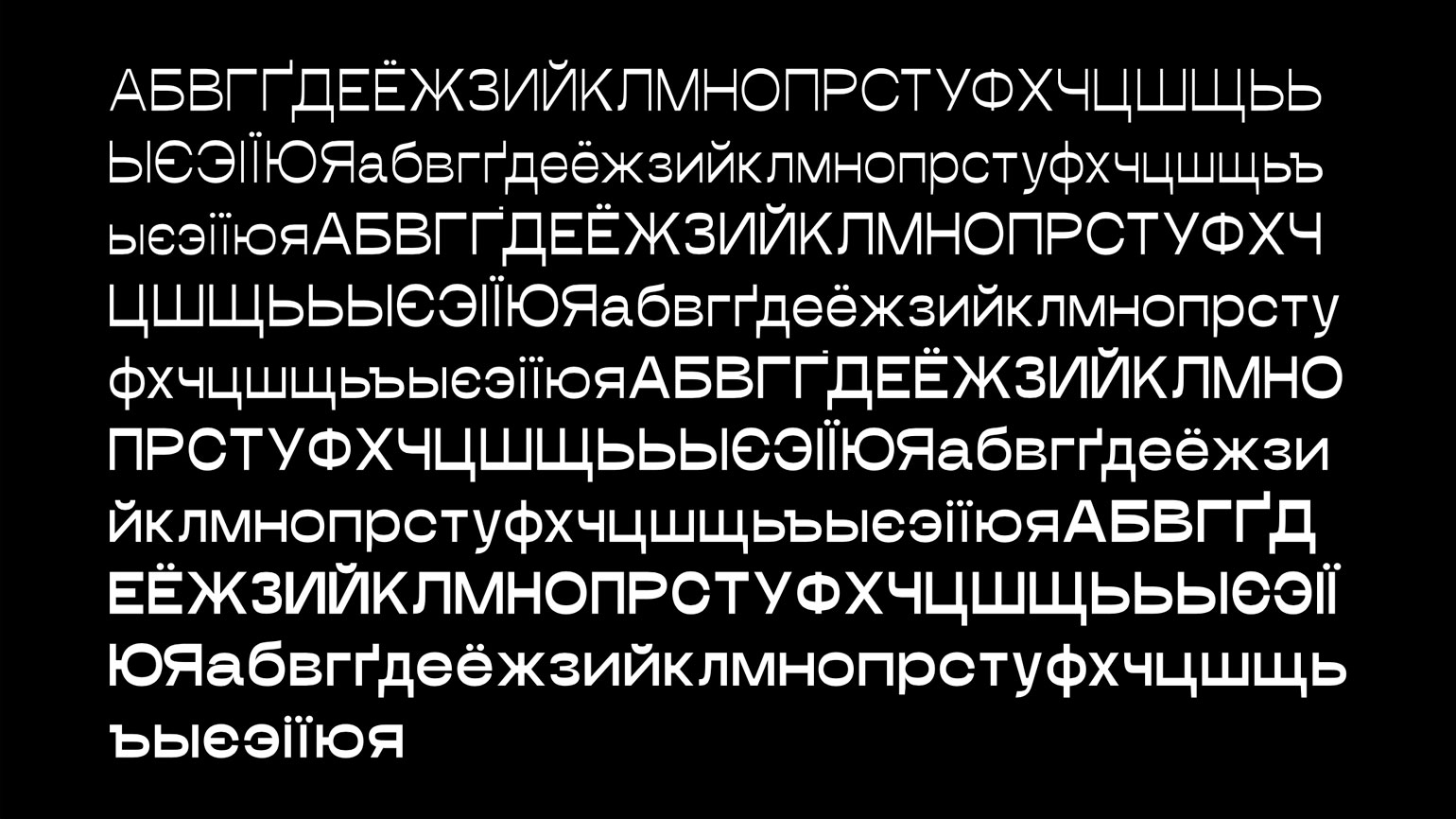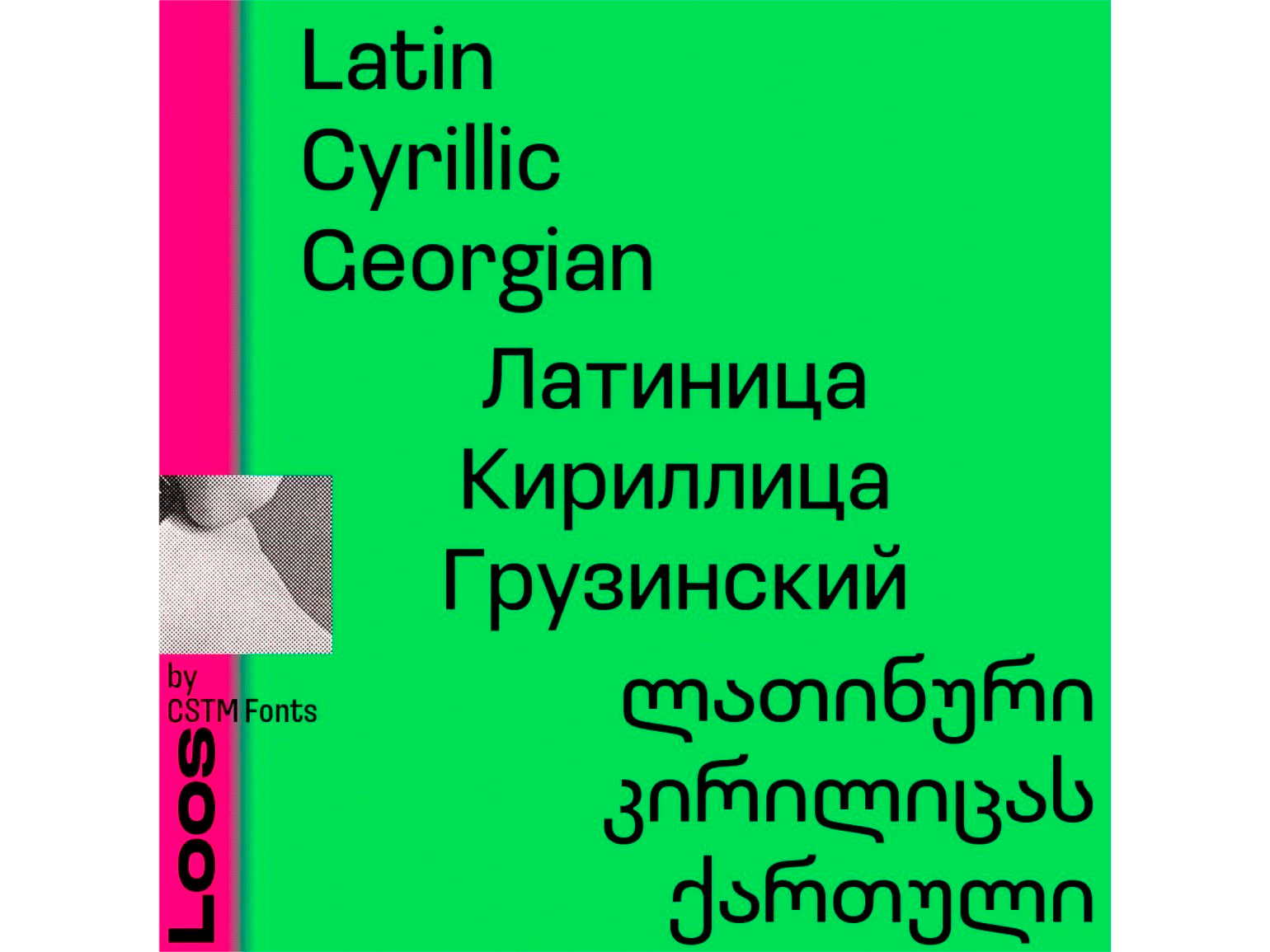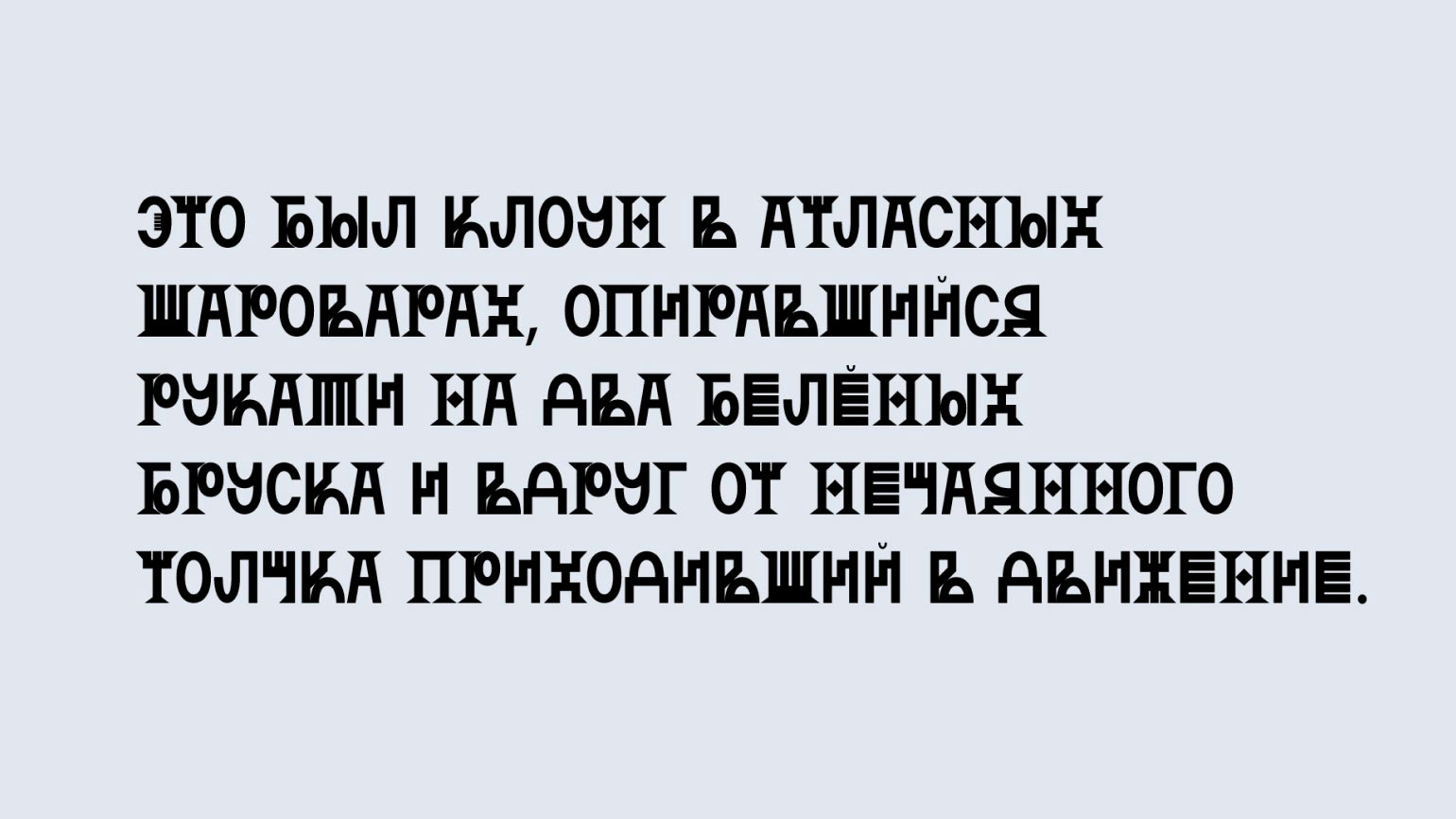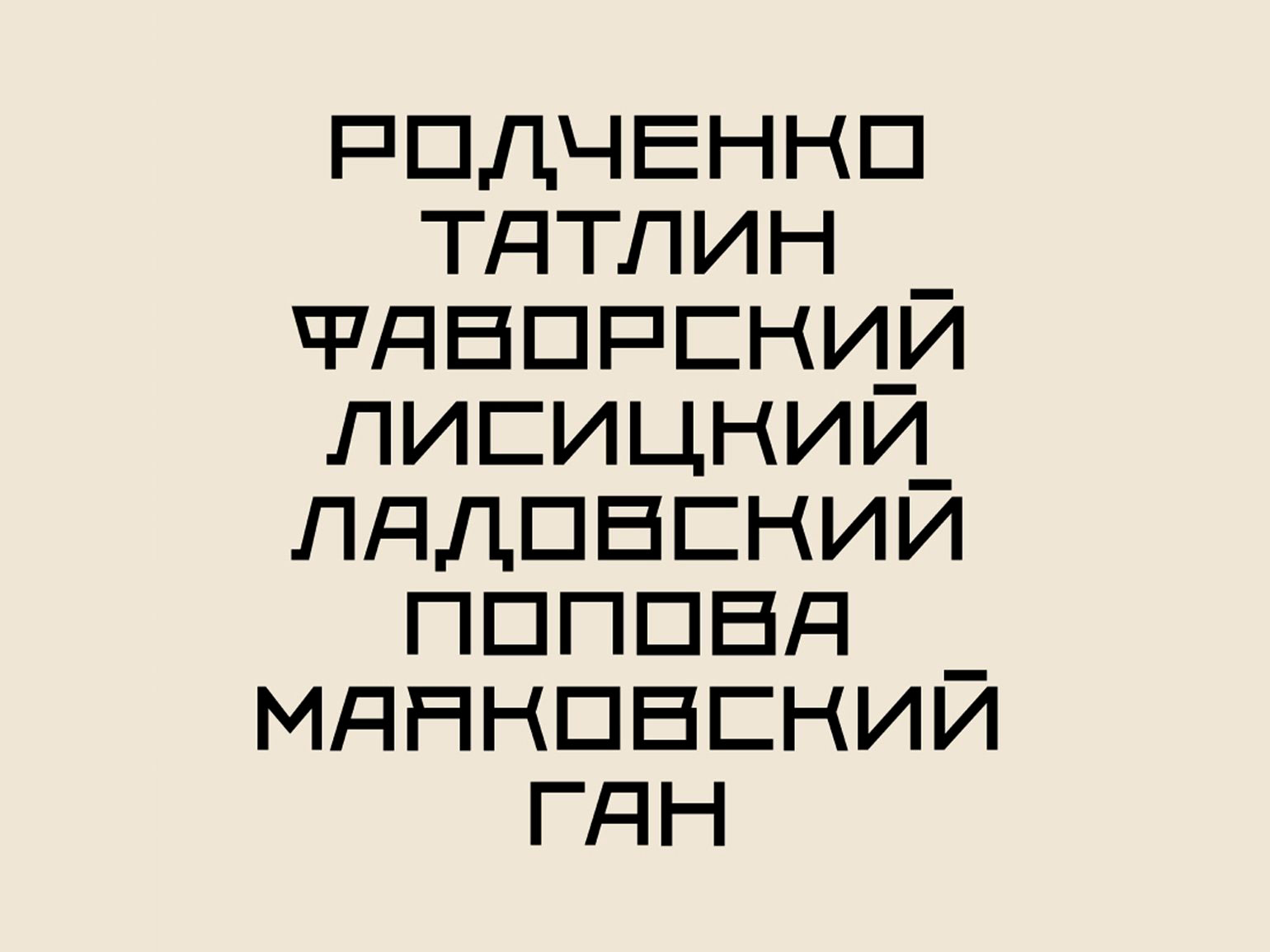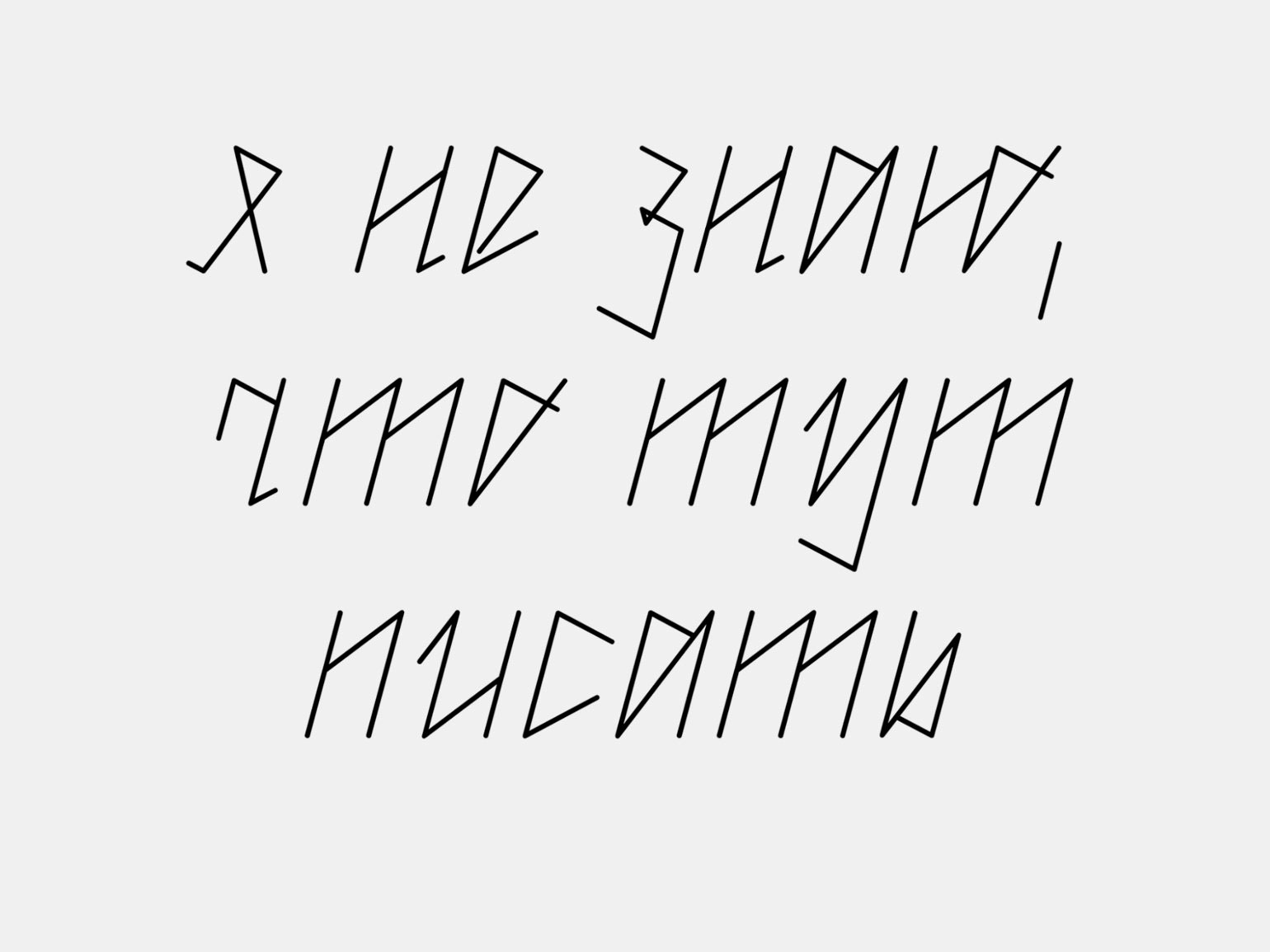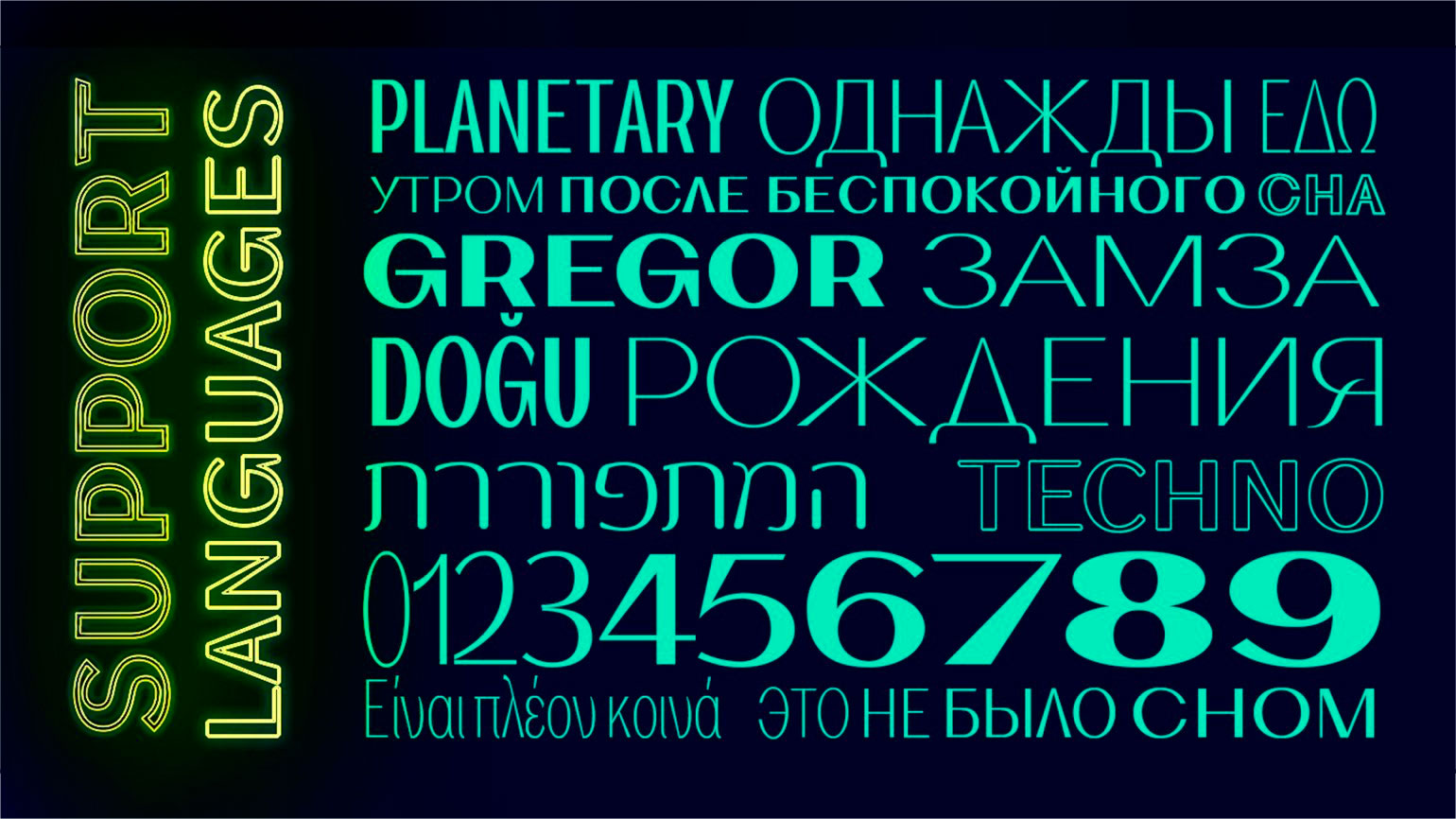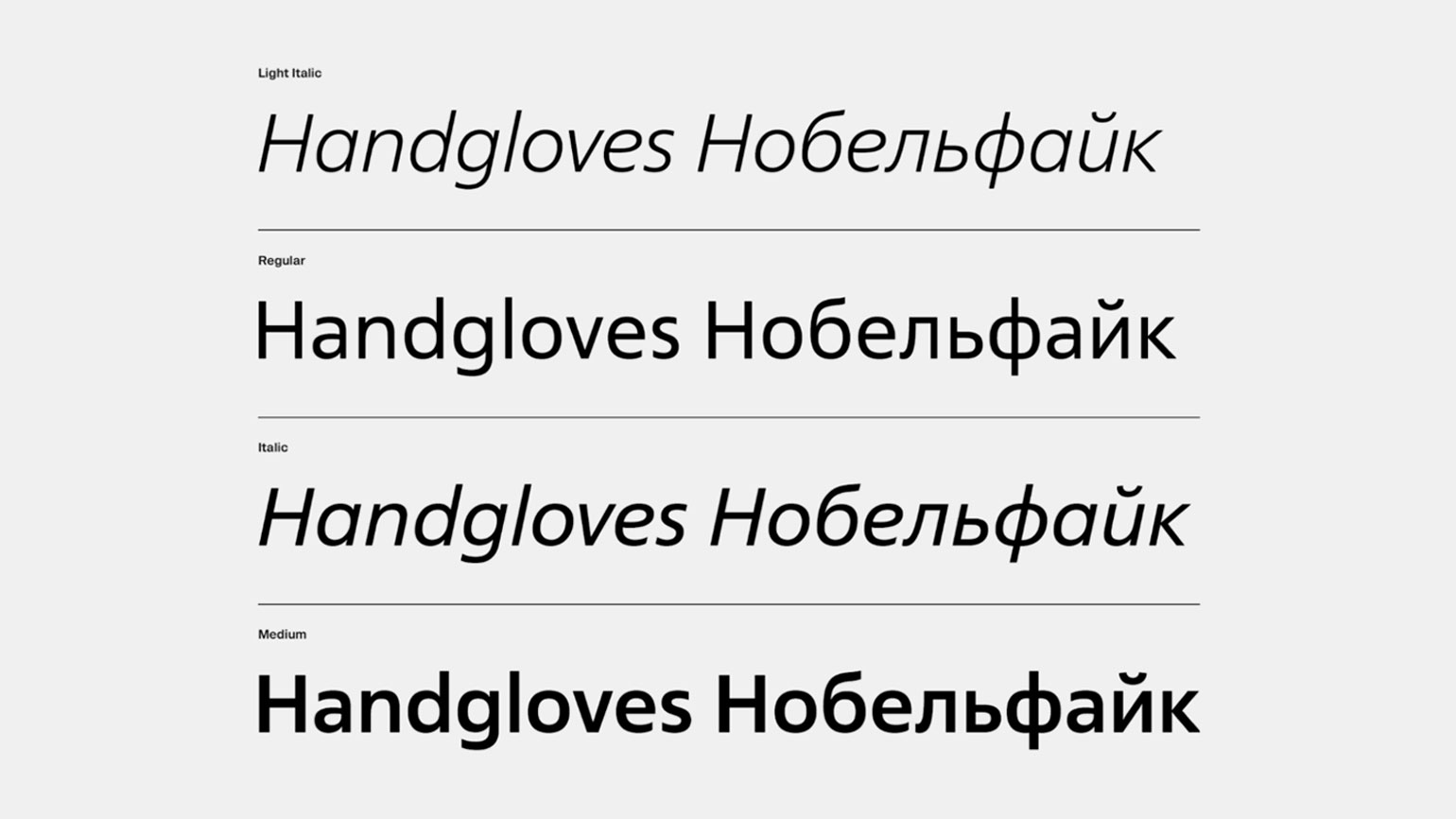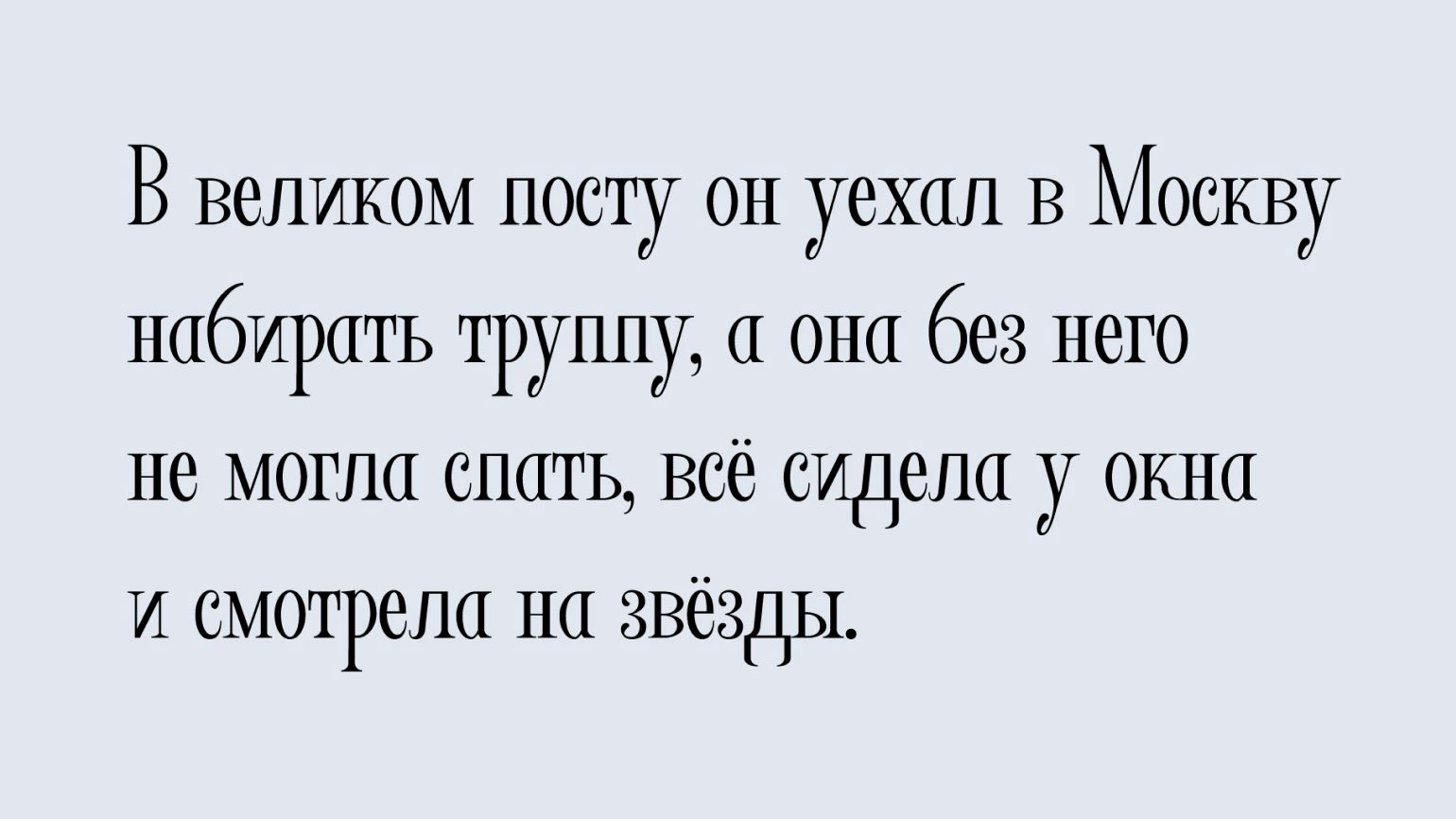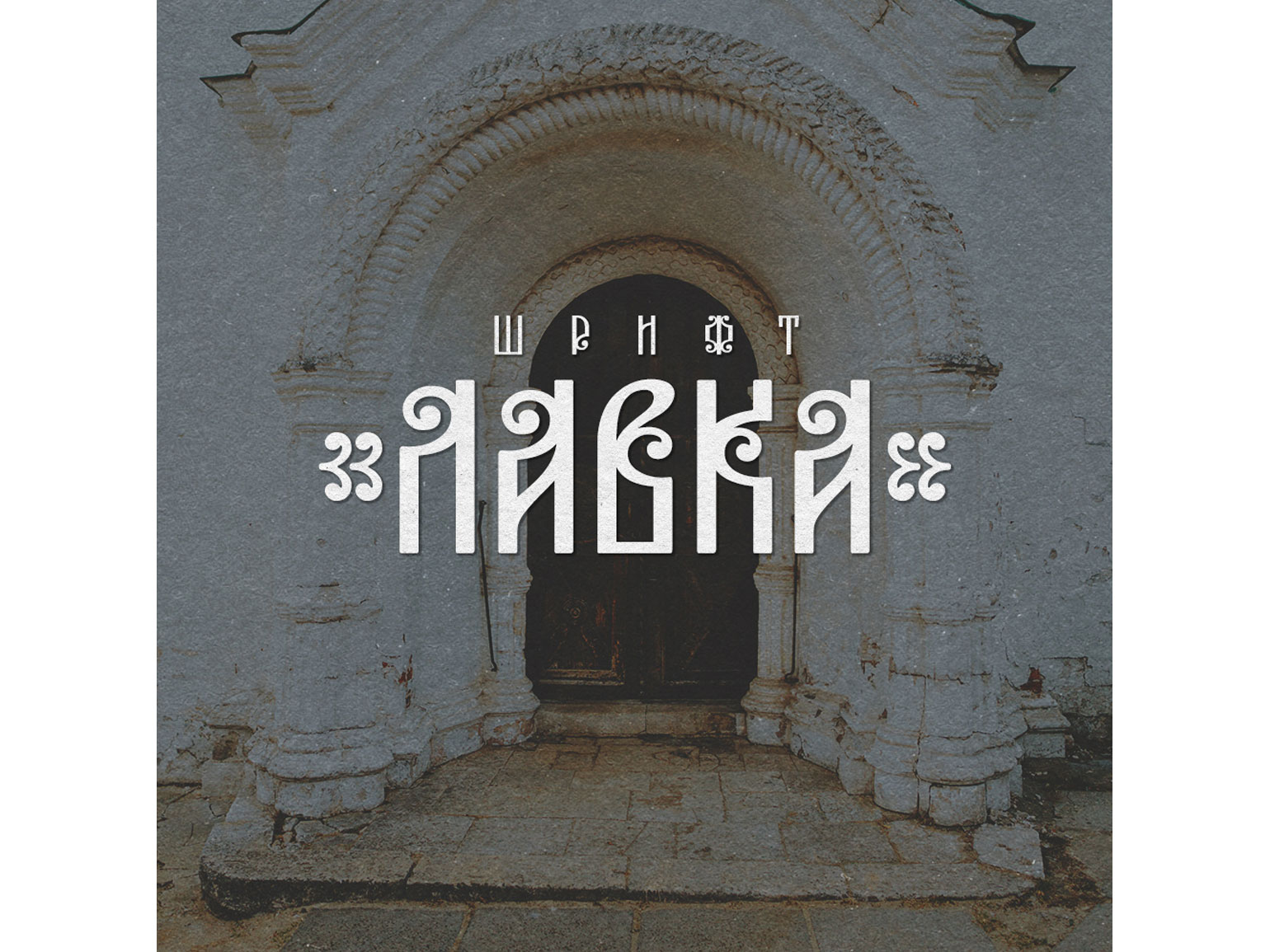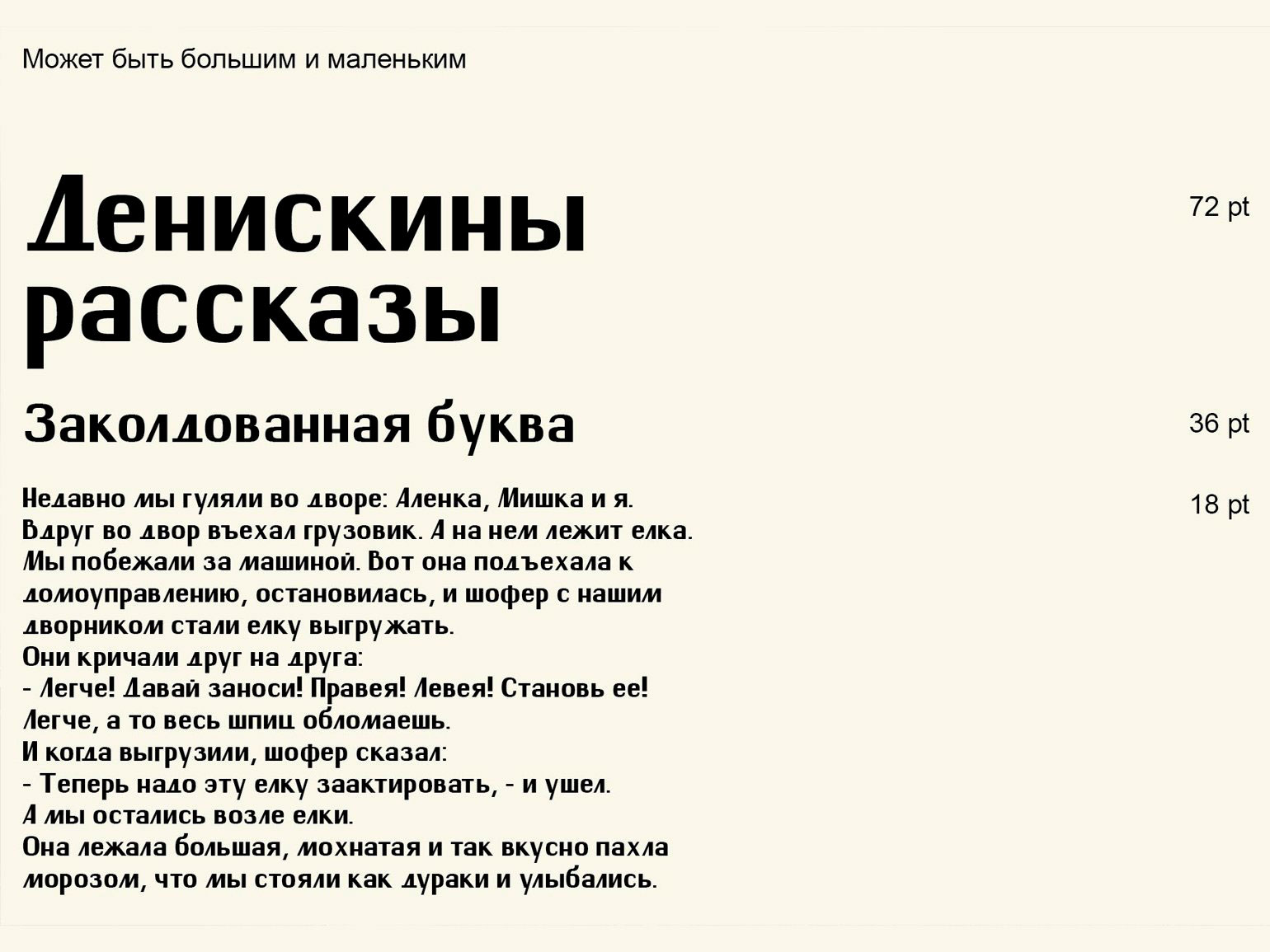
Кириллица: 16 бесплатных и платных шрифтов для ваших проектов
Шрифты в русском стиле, рукописные, зауженные и в духе авангарда.
В этой подборке вы найдёте интересные шрифты с кириллицей.
Kwele
Kwele — декоративный шрифт c треугольными засечками от российского дизайнера под псевдонимом Qaes Al-atoom. Поддерживает кириллицу и латиницу, распространяется бесплатно для личного и коммерческого использования.
Fornire
Fornire — зауженная антиква от индонезийского дизайнера Анвара Патихана (Anwar Patihan). Всего в гарнитуре четыре начертания, бесплатно доступно только Light.
Lavka
Lavka — шрифт, стилизованный под кириллическую вязь от дизайнера Дмитрия Тектова. Имеет одно начертание, бесплатен как для личного, так и для коммерческого использования.
TA Modern Times
TA Modern Times — контрастный гротеск, разработанный азербайджанцем Туралом Алиевым (Tural Aliyev). В семейство входит огромное множество начертаний. Бесплатно доступно только Extra Light, зато в шести ширинах — от Ultra Condensed до Ultra Expanded.
Boris
Boris — декоративный шрифт без засечек, разработанный Ксенией Герник. Все буквы построены на рубленых формах и тяготеют к прямоугольникам. Имеет одно начертание, бесплатное для личного и коммерческого использования.
Vkhutetype
Vkhutetype — геометрический гротеск в стиле двадцатых годов прошлого века от Всеволода Власенко и Петра Банкова. Шрифт вдохновлён эстетикой ВХУТЕМАСа и используется в образовательном проекте «ВХУТЕМАС.academy». Бесплатный только для личного использования.
Arina
Arina — антиква с узкими пропорциями и острыми засечками, вдохновлённая вязью и уставом. Автор шрифта — Михаил Власов. Проект представлен в одном начертании, доступном бесплатно для личных и коммерческих целей.
Durik
Durik — узкий контрастный гротеск, вдохновлённый советскими леттерингами с плакатов. Разработан Надей Найдёнкиной. Подходит для заголовков и основного текста, бесплатный для личного и коммерческого использования.
Tonky
Tonky — монолинейный акцидентный рукописный шрифт от Полины Залевской с поддержкой кириллицы и латиницы. Доступен в одном начертании, бесплатен для личного и коммерческого использования.
Zloy
Пример использования жирного акцидентного шрифта с острыми засечками Zloy
Zloy — жирная акцидентная антиква с острыми массивными засечками от Дарьи Петровой. От 1600 ₽ за начертание.
Menorah Grotesk
Menorah Grotesk — гротеск с обратным контрастом, который совмещает в себе сразу три алфавита: кириллицу, латиницу и иврит. Подходит для заголовков и основного текста, есть четыре начертания. Цена стартует от 25 долларов за начертание. А ещё есть тестовая версия: шрифт нельзя публиковать в проектах, но можно оценить, как он будет выглядеть в макете.
Loos
Loos — закрытый гротеск, черпающий вдохновение из модернистских гротесков прошлого столетия. Имеет огромное количество начертаний, от Compressed до Extended и от Thin до Black. Поддерживает латинский, кириллический и грузинский алфавиты.
Шрифты брендов и операционных систем
IZH 260
Пример использования фирменного шрифта Ижевска IZH 260
IZH 260 — официальный шрифт Ижевска. Гарнитуру разработали под руководством студии Paratype летом 2021 года. Сделали два начертания — для заголовков и основного текста. Шрифт используют на муниципальных сайтах и в городской навигации. IZH 260 бесплатный, но получить его можно только по заявке — для проекта в Удмуртии.
PT Astra Fact
PT Astra Fact — новое шрифтовое семейство от Paratype для российской операционной системы Astra Linux. Изначально дизайнеры хотели использовать Verdana, но с получением лицензии возникли сложности из-за санкций.
Шрифт доступен в качестве системного на Windows 11.